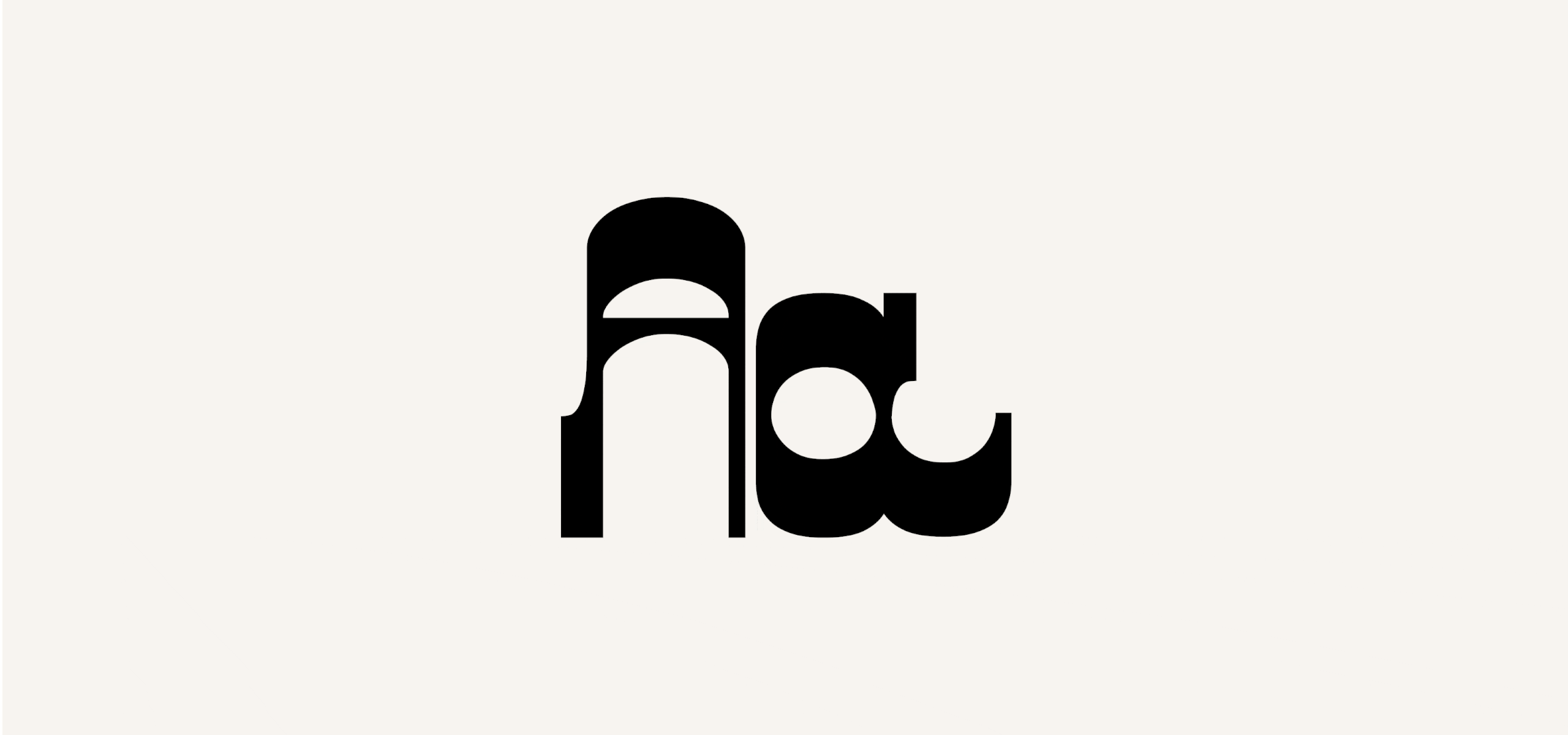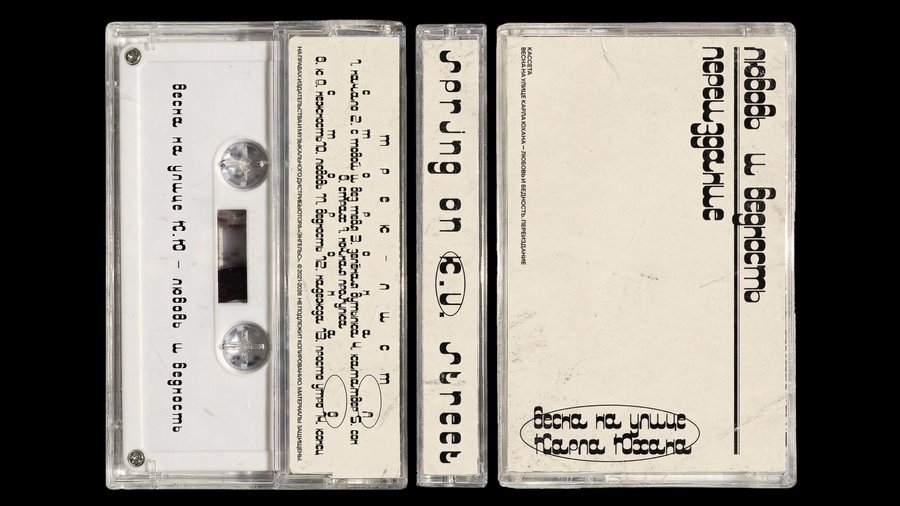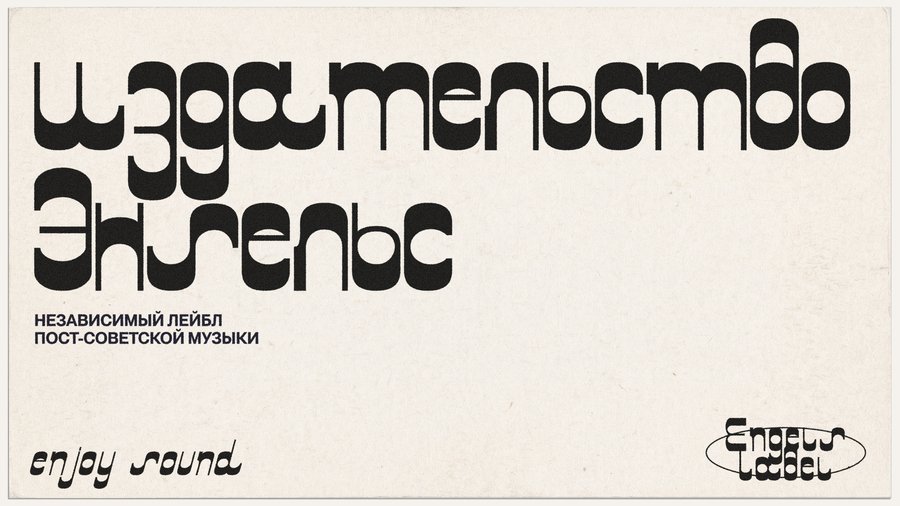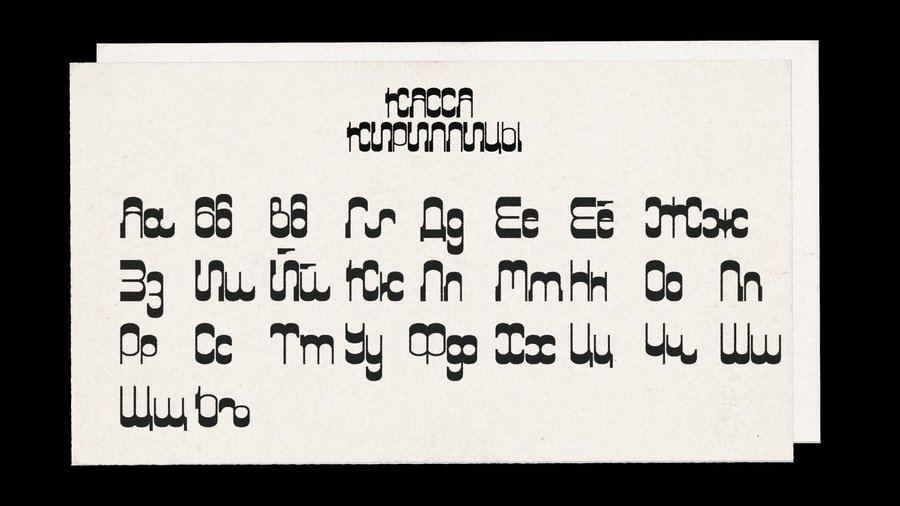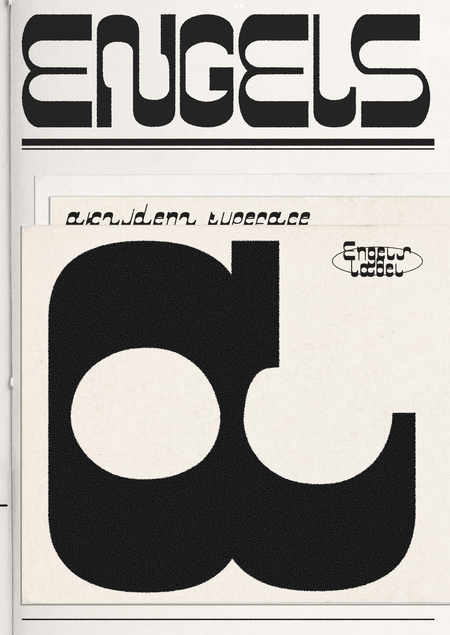
ENGELS — модульный шрифт, вдохновленный советскими акциденциями с обратным контрастом. Пластика шрифта собрана из модулей-примитивов: прямоугольника и ¼ окружности.